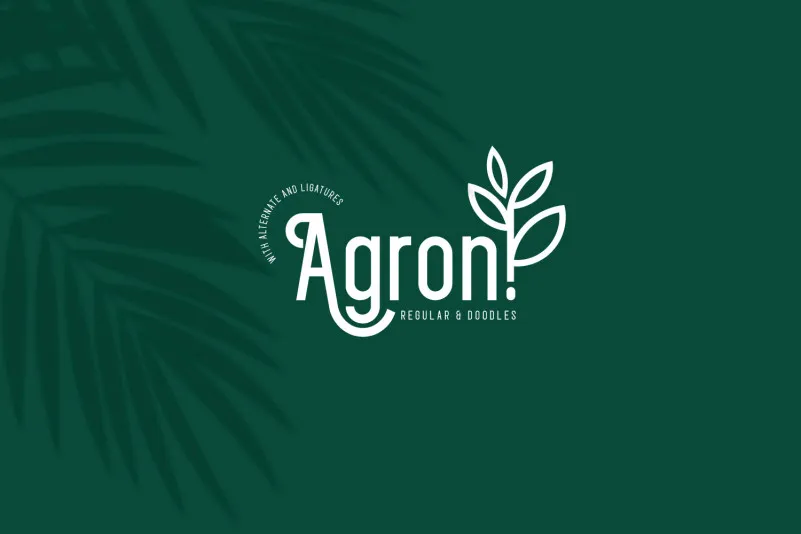
Agron Display Font – Download Grátis
Agron Display Font é uma fonte sans-serif projetada com a mistura de estilos moderno e vintage. Esta fonte oferece ligaturas, letras alternativas e desenhos que lhe proporcionam infinitas possibilidades de design. Ideal para sua prática, seja ela posters, logotipos, revistas, capa, banners ou camisetas, ou até mesmo trabalhos de arte em grande escala. Esta font é perfeita para quem busca um efeito moderno com toques nostálgicos. Perfect para qualquer projeto visual que busque expressar uma combinação única de design gráfico atualizado e vintage.